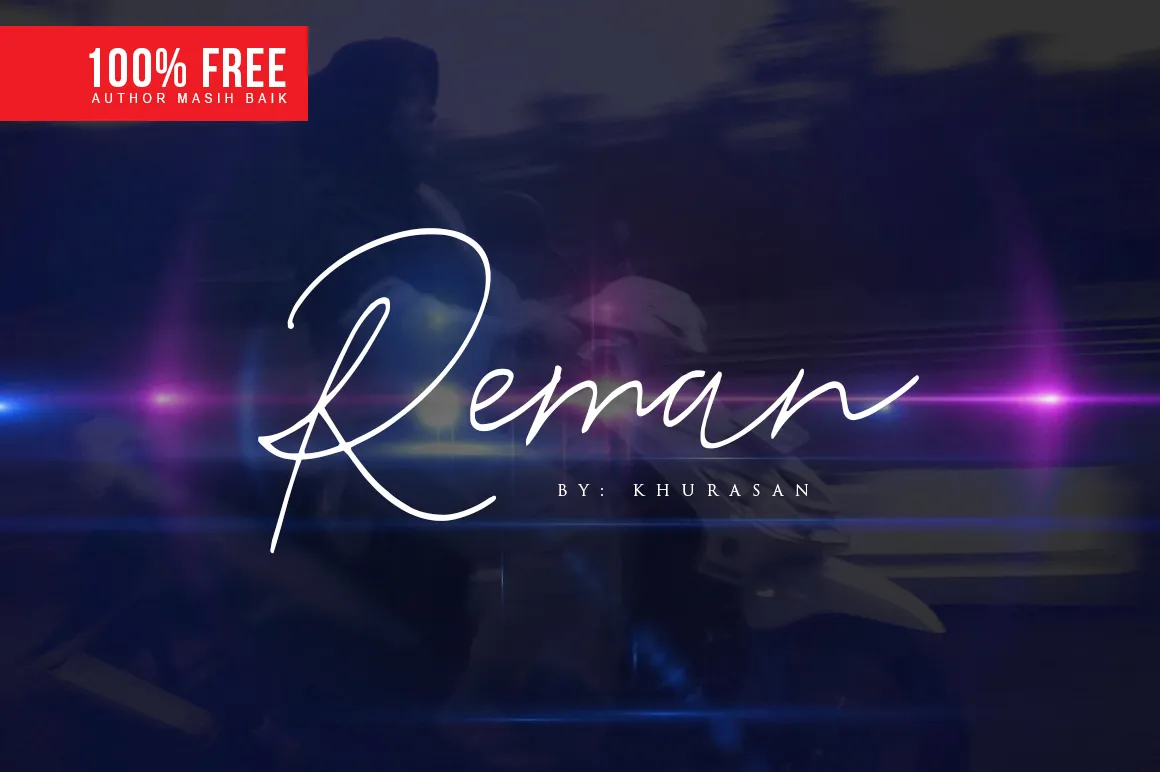
Reman Script Font – Download Grátis
A Reman é uma fonte escrita a mão com traços normal e italico, resultante de uma arte feita inteiramente por mãos humanas. Possui uma característica natural que transmite sensações de autenticidade e conforto visual. Esta fonte foi criada pelo designer Syaf rizal e compartilhada para um uso diversificado em projetos de design, incluindo logos e marcas, desenhos de casamento, postagens nas redes sociais, anúncios e outros designs de produtos. Com a Reman, você pode encontrar harmonia de tipografia que se adequa a uma ampla variedade de necessidades de projeto gráfico. Suas linhas delicadas e o uso natural das letras ajudam a criar um design visual que é tanto profissional quanto pessoal. A Reman é perfeita para aqueles que valorizam um touch artesanal em seus projetos, seja para uma simples postagem nas redes sociais ou para uma identidade de marca complexa.